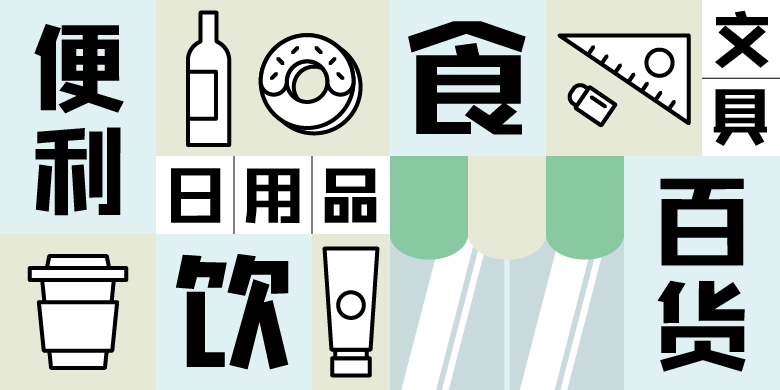
方正字悦黑
方正字悦黑,这款字体结构工整、笔画清晰,兼顾美观与易读性,适用于标题、正文、海报、包装、LOGO 等多种场景。字形优雅稳定,风格百搭耐看,适配日常排版与创意设计,让文字呈现更舒适、更具质感。方正字悦黑一笔一画,皆是细节,以均衡的比例、流畅的线条打造舒适视觉体验,字形端正大气,风格简约现代。无论是商业设计、品牌宣传还是日常排版,都能轻松驾驭,让文字更有格调与力量。方正字悦黑字体下载。
做这款字体时,初衷是归纳和拆分字体部件,也就是在记录组合字的部件及归纳的同时设计出了这款直线型字体。
这款字体定位于个人在字体设计中的工具字体,可适用于海报招贴、视频、产品包装等应用领域。